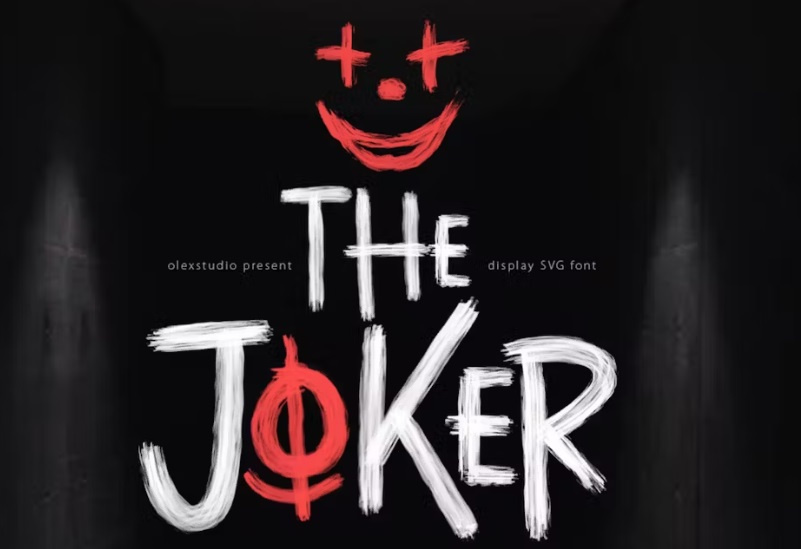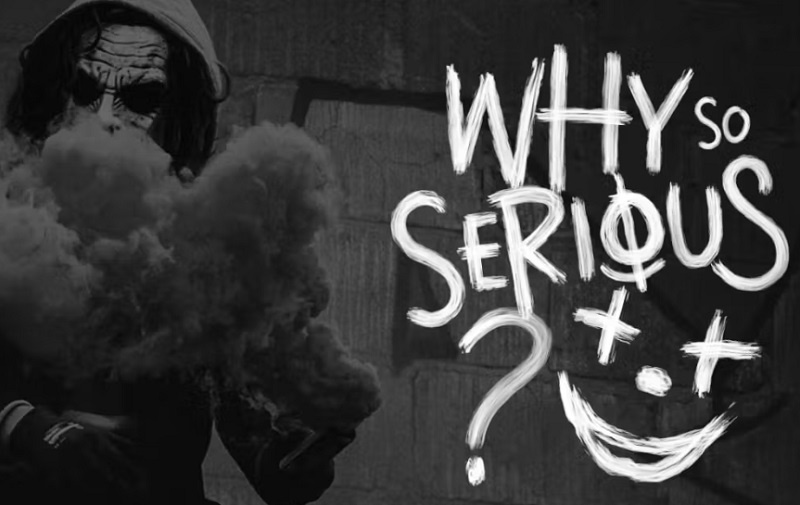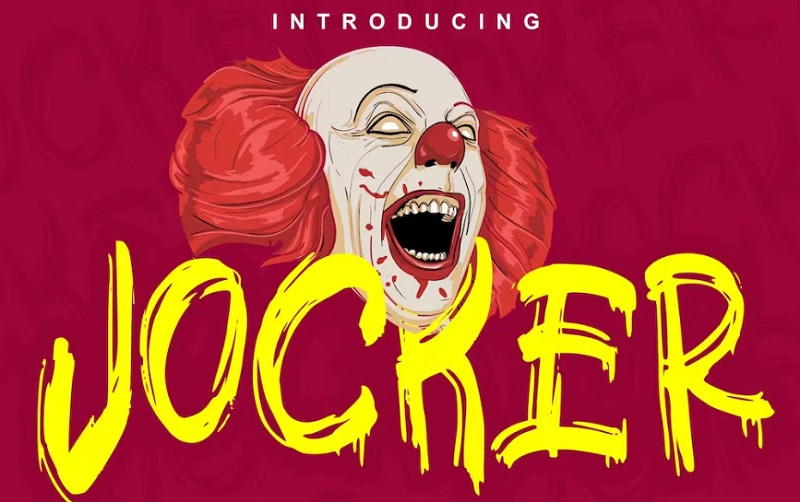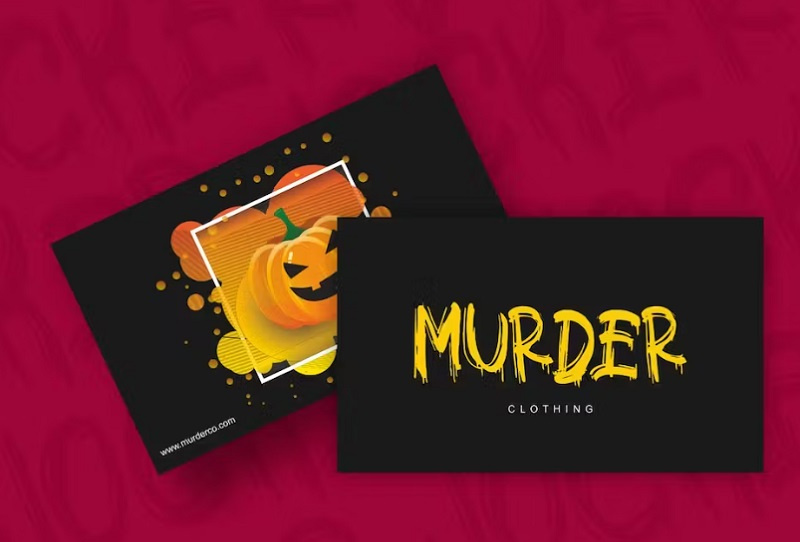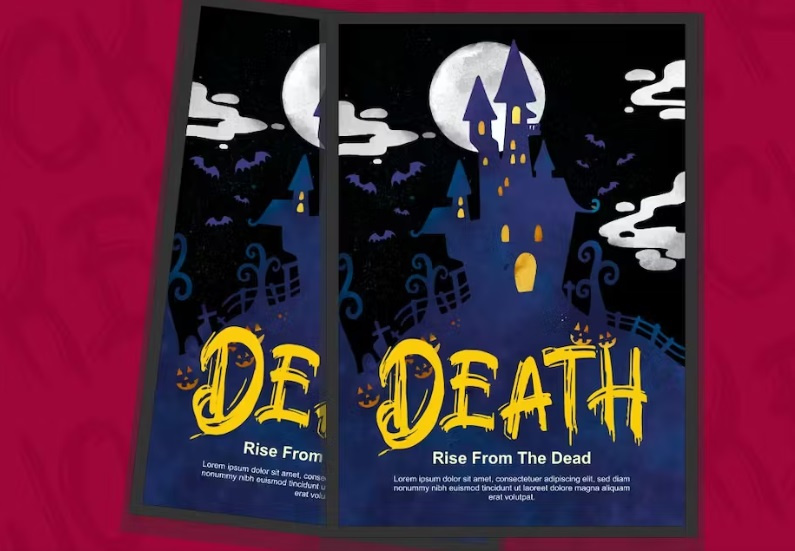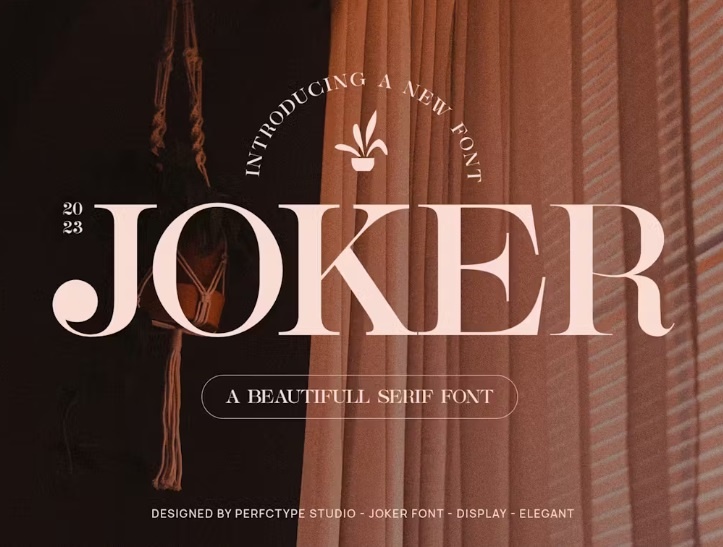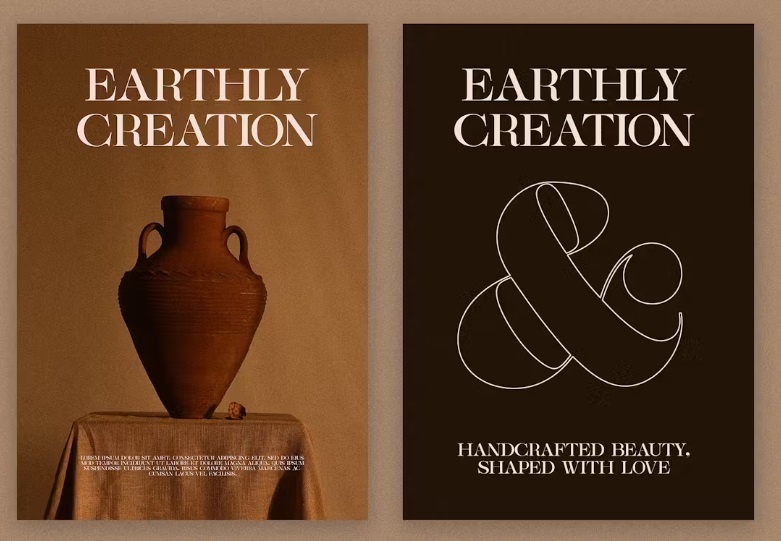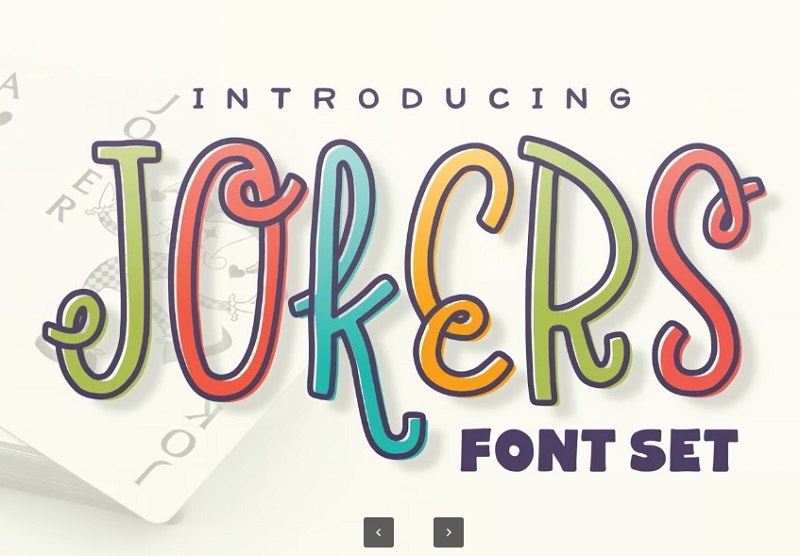
فونت انگلیسی جوکر از جی اف ایکس دانلود. این مجموعه شامل 4 فونت انگلیسی برای طراحان و گرافیست ها می باشد. فونت جوکر به انگلیسی مناسب برای تمام طرح های شما، دعوت نامه، کتاب، مواد برندسازی، لوگو، تی شرت، پوستر و تمام طراحی های پروژه دیگر زیبا به نظر می رسد. اگر برای طراحی های خود به فونت جوکر نیاز دارید بدون شک یکی از فونت های زیبا و کاربردی می باشد.
فونت جوکر به انگلیسی یک فونت منحصر به فرد و بسیار زیبا برای طراحی برند و لوگو است. این نوع فونت برای نیازهای مختلف طراحی مثل برندسازی، لوگو، طرح های پوستر، پست های شبکه های اجتماعی، تبلیغات، بسته بندی محصولات، طرح های محصول، برچسب ها و ... مناسب می باشد.
فونت اسم جوکر به انگلیسی Joker
فونت اسم جوکر به انگلیسی با نام Joker از جی اف ایکس دانلود. این فونت زیبا مناسب برای طراحی پوستر و بنر فیلم، طراحی لوگو، طراحی گرافیک و تایپوگرافی و غیره می باشد.